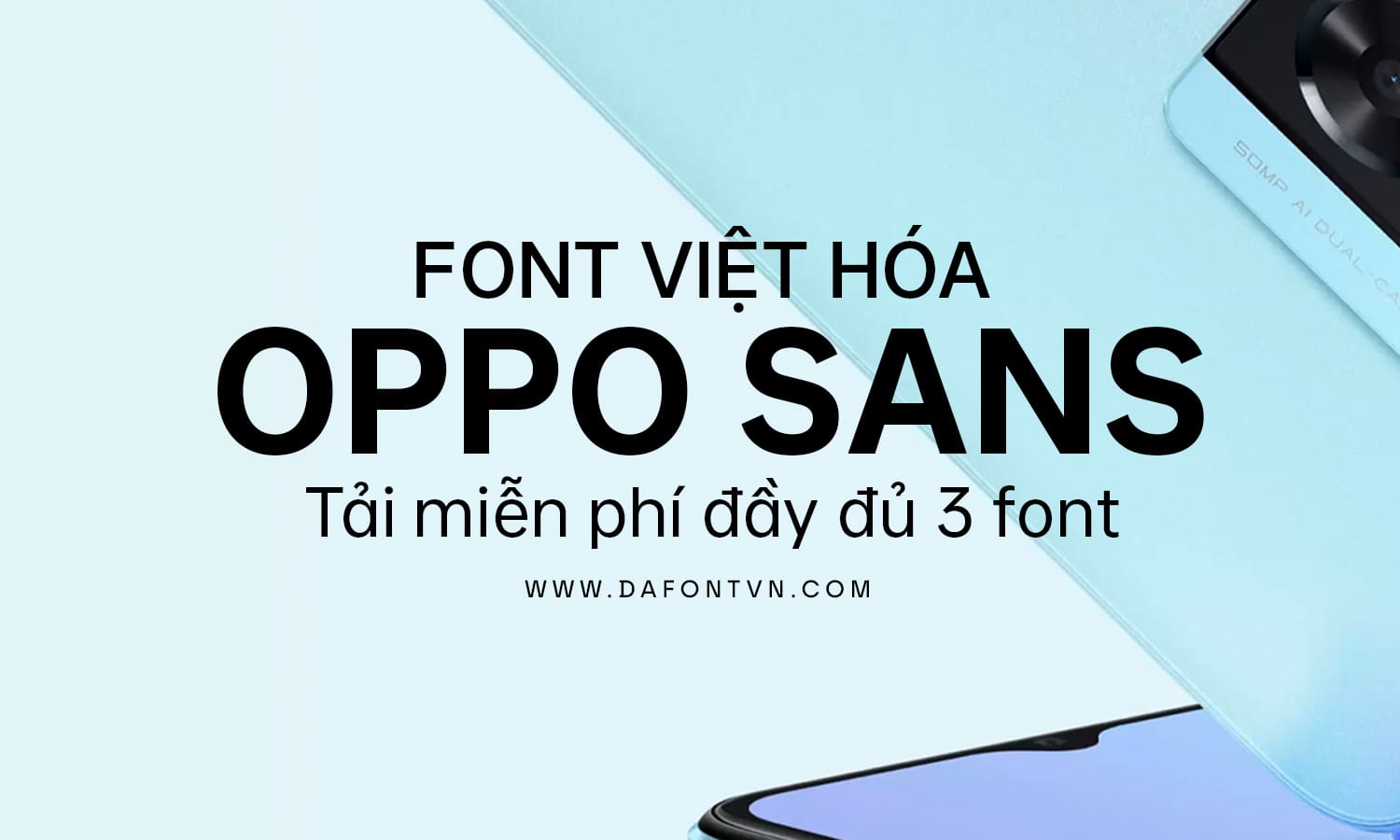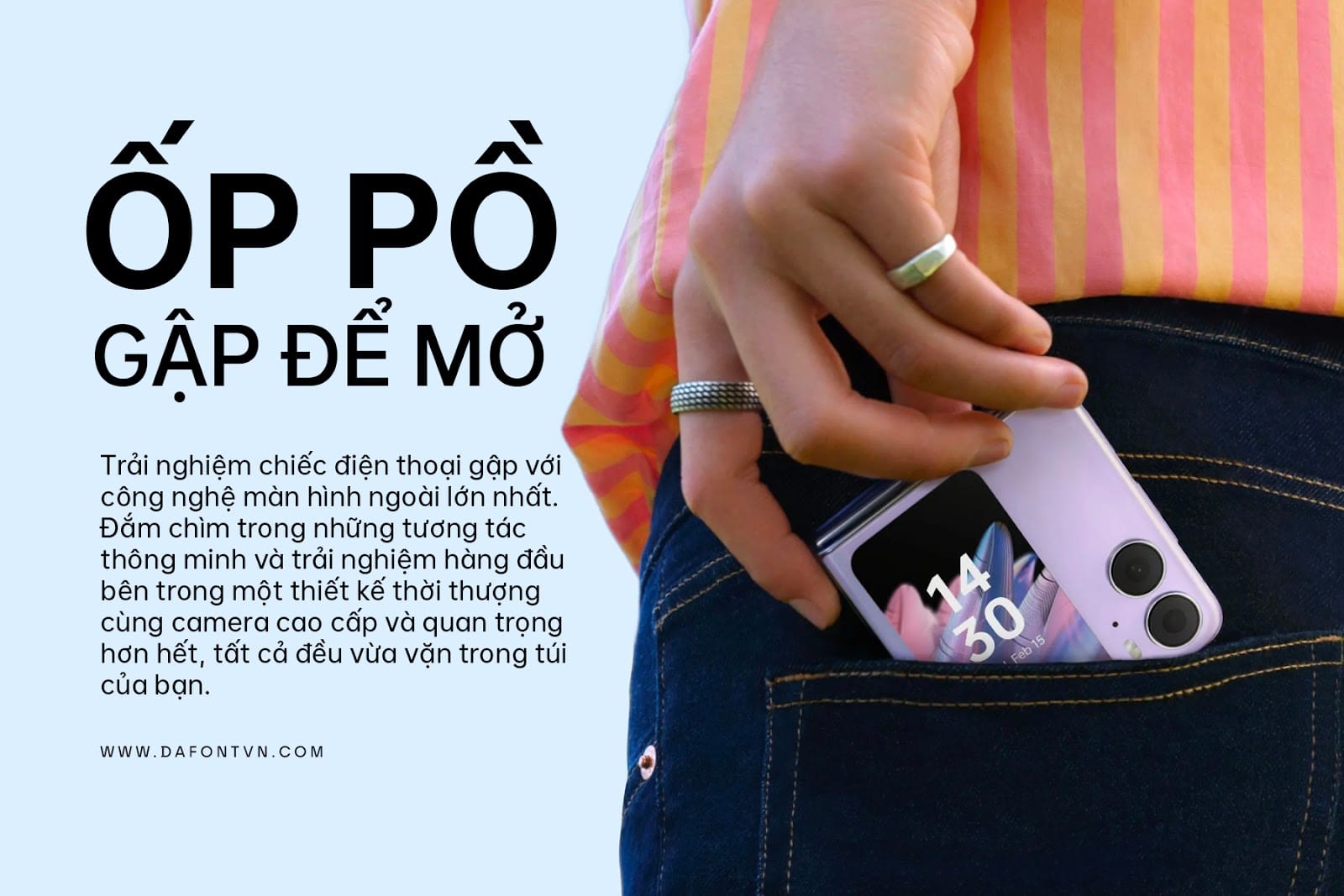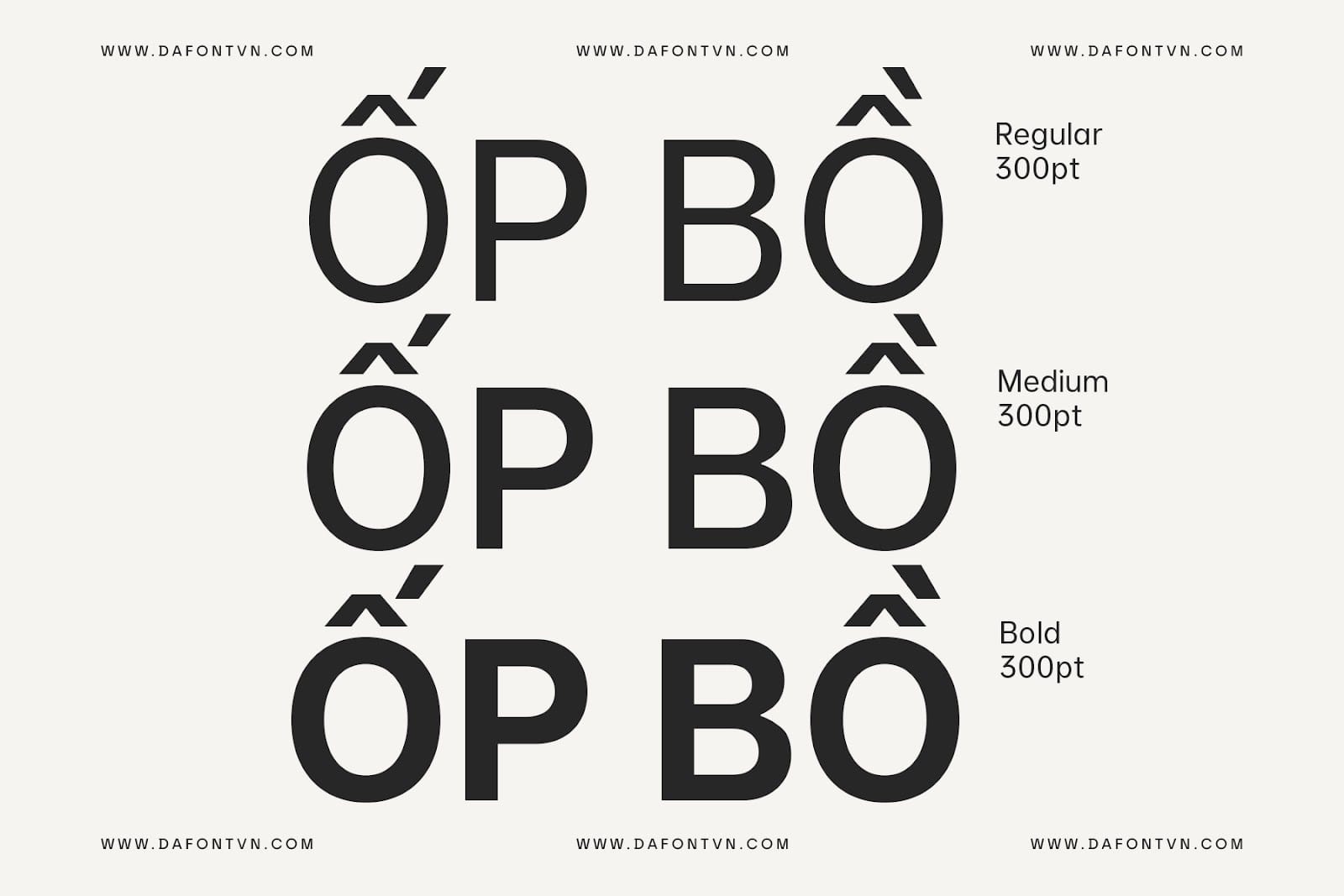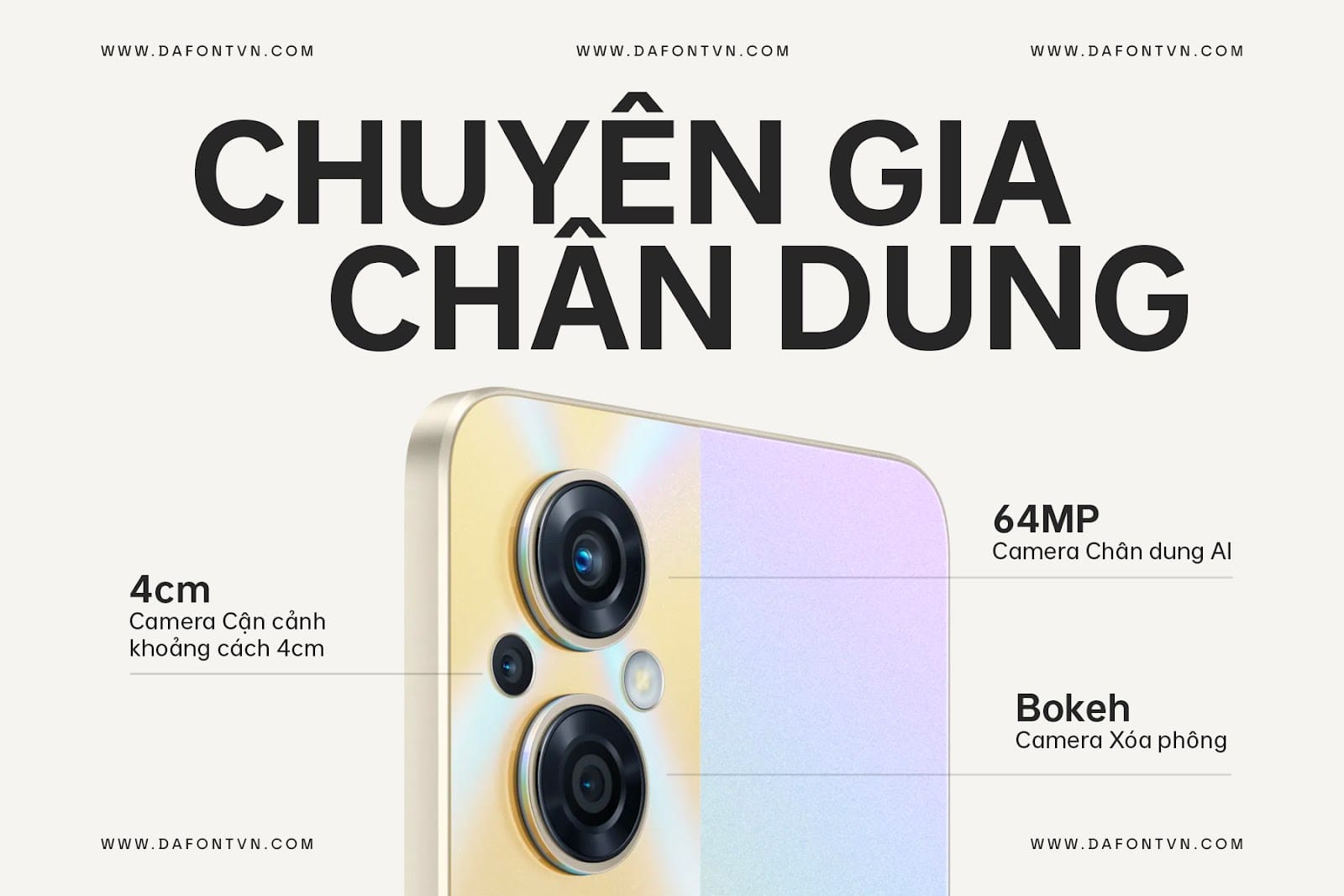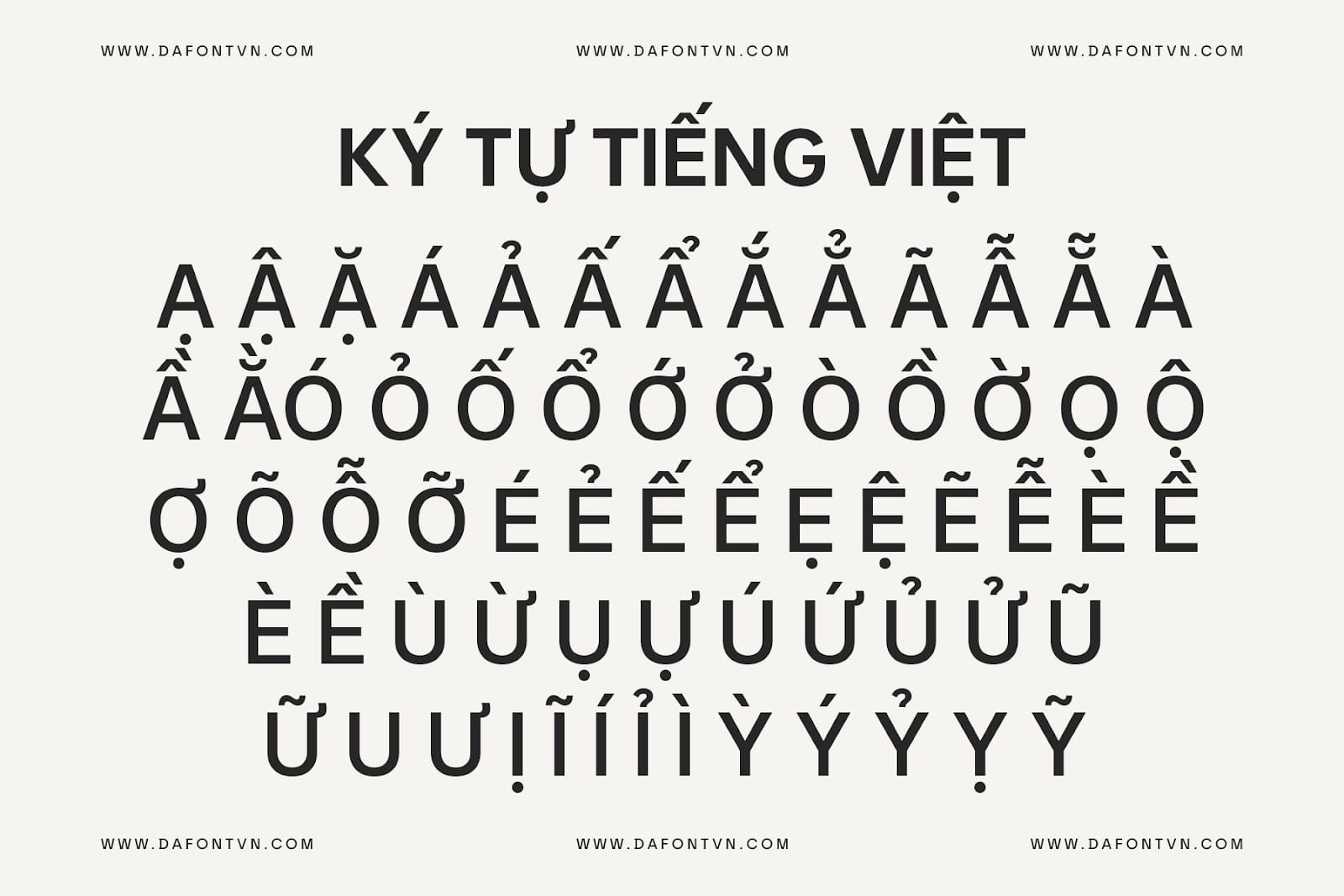
OPPO Sans là font chữ sử dụng cho thương hiệu của OPPO tại Việt Nam, bộ font chữ này được dùng cho hầu hết các ấn phẩm, quảng cáo, website, ứng dụng… Đây là kiểu chữ sans serif cơ bản so với hầu hết các font chữ khác, bộ font OPPO Sans việt hóa bao gồm 3 kiểu (Regular, Medium và Bold).3 kiểu font này tạo ra với các tùy chọn tối giản để dễ dàng sử dụng trên hầu hết các nội dung. Đây là bộ font tận dụng lợi thế của OpenType và giúp mọi người đạt được giao diện hoàn toàn tùy chỉnh. Nó hoàn hảo cho logo, dự án xây dựng thương hiệu, tiêu đề, áp phích, văn bản nội dung và bất cứ thứ gì bạn muốn.